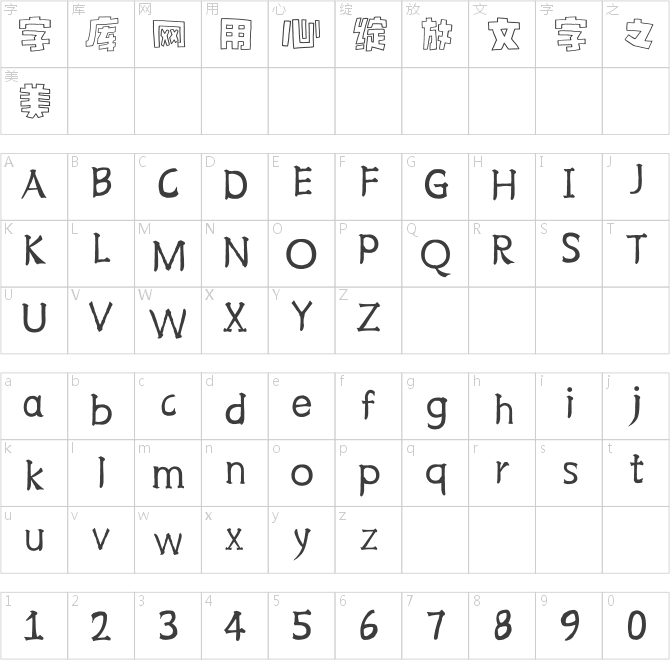
字体名称: 姥姥说媒韩艾璇
姥姥说媒韩艾璇小艾双钩简体
小艾双钩简体是一款逗趣可爱、动感活泼的创意美术标题字。它的字形变化多样,笔画掏空,粗细对比强烈,组合起来富有节奏感。的字形多变,依据字体结构而呈现出或长或方的节奏变化,十分俏皮可爱。
姥姥说媒韩艾璇小艾双钩简体字体小艾双钩简体字库是一款让人赏心悦目、百看不厌的中文字体,适合各类广告和产品包装设计应用,字体大小16.54MB,格式为ttf字体,上传用户是邯郸字库,作者/版权方为韩艾璇